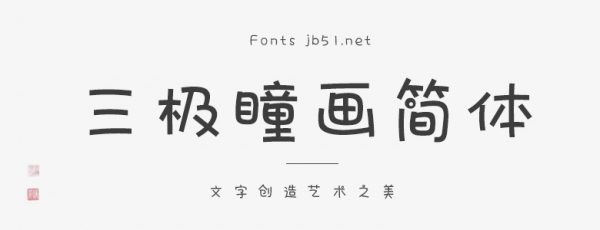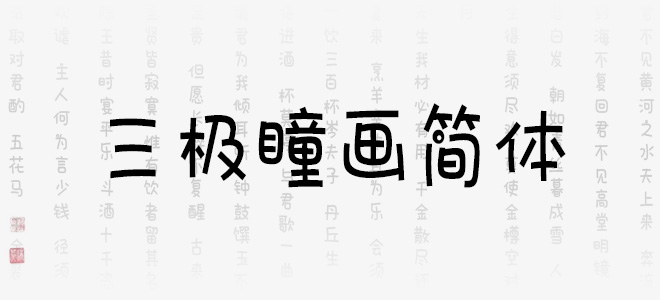
三極瞳畫(huà)簡(jiǎn)體運(yùn)用童趣設(shè)計(jì),部分點(diǎn)畫(huà)用立體圓點(diǎn),使得字形生動(dòng)活潑,整體風(fēng)格使用兒童書(shū)寫(xiě)的輕松隨意,筆畫(huà)簡(jiǎn)潔隨性。字形飽滿拙趣,明快可愛(ài)。適用于少兒類(lèi)讀物、書(shū)刊、品牌廣告、母嬰用品包裝設(shè)計(jì)以及社交網(wǎng)絡(luò)個(gè)性化用字。
三極瞳畫(huà)簡(jiǎn)體